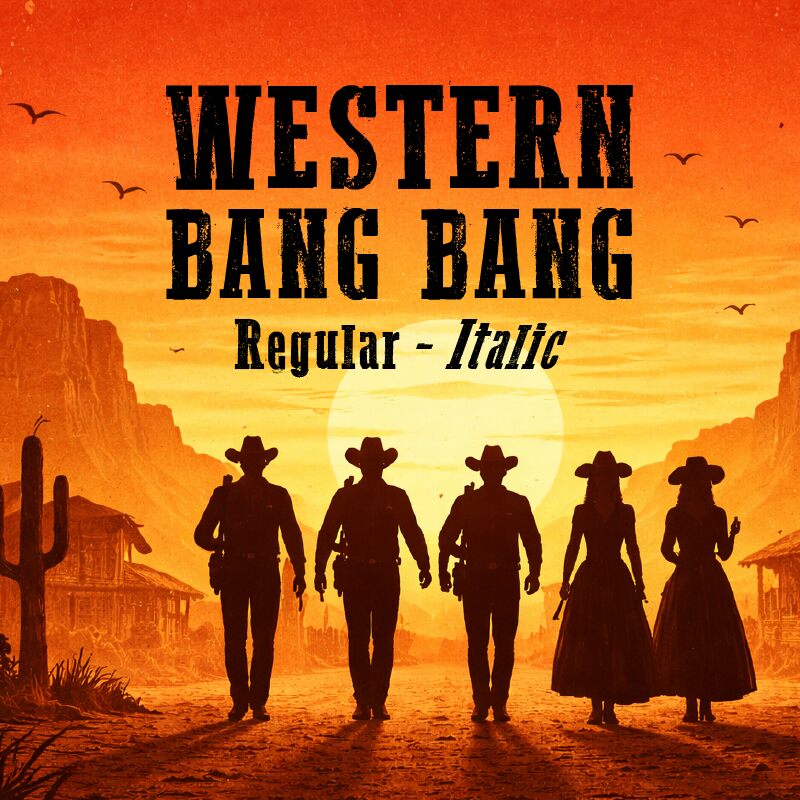
Western Bang Bang Italic, di Galdino Otten, è un font display gratuito in stile Western che porta con sé lo slancio inclinato dei vecchi poster di frontiera. Le lettere mescolano tratti larghi a forma di cuneo con bordi scheggiati e consumati, rendendo il carattere polveroso, drammatico e leggermente grezzo, senza però sacrificare la sua silhouette audace.
Si adatta perfettamente al branding in stile saloon, ai flyer per rodeo, ai poster di festival country, alle copertine di libri e ai titoli che richiedono un tocco immediato di atmosfera da fuorilegge. Essendo un font gratuito, è ideale anche per loghi brevi, intestazioni di menu e packaging, dove quel movimento inclinato e dall'aspetto usurato conferisce anche a poche parole una presenza incisiva e vissuta.